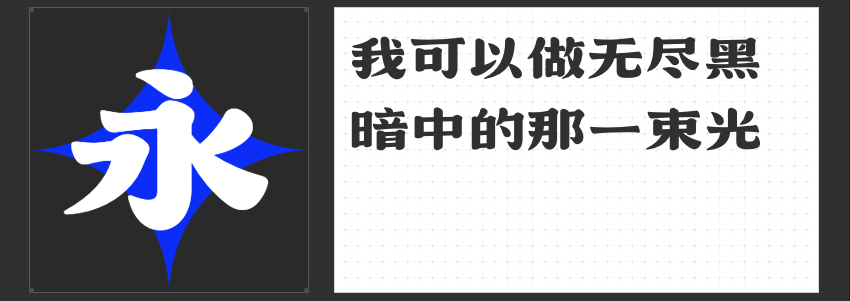
小雪节气设计精选字体推荐:雅致与温馨的视觉盛宴
随着冬日的脚步悄然临近,小雪节气以其独有的静谧与纯洁,成为了设计中寻求温馨与雅致氛围的绝佳灵感来源。在这个银装素裹的时节,选择合适的字体不仅能够增强视觉美感,更能深刻传达节气的文化韵味。今天,就让我们一起探索四款特别适合小雪节气设计的字体,它们各自以独特的风格,为冬日设计增添一抹不可多得的温度。
1.高手兵克柔书体
以其温婉流畅的笔触,仿佛初雪覆盖下的嫩枝,轻柔而不失力度,完美契合小雪时节那份细腻与柔和。这款字体在设计海报或邀请函时,能够营造出一种温馨而又不失高雅的氛围。
2.高手兵克逍遥体
则带着一种洒脱不羁的气质,如同冬日里偶尔露出的晴朗天空,明媚而自由。它适合用于标题或标语,为设计作品增添一抹灵动与活力。
这款字体以苍劲有力的笔画,展现出冬日里坚韧不拔的生命力。无论是简体中文还是繁体,都能在设计中展现出一种沉稳与力量,适合用于传达小雪节气的深刻寓意。
4.高手字斋树高行书
其行书风格行云流水,如同林间小径上的轻盈步伐,既展现了自然界的和谐之美,又蕴含了深厚的文化底蕴。这款字体在各类设计中都能成为点睛之笔,为小雪节气带来一抹诗意与远方。
综上所述,这四款字体各具特色,无论哪款,都能在小雪节气的设计中,找到属于自己的舞台,共同编织出一场视觉与情感的双重盛宴。